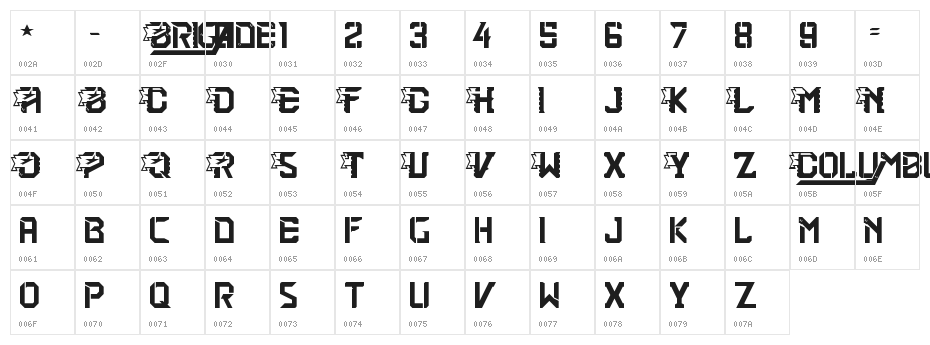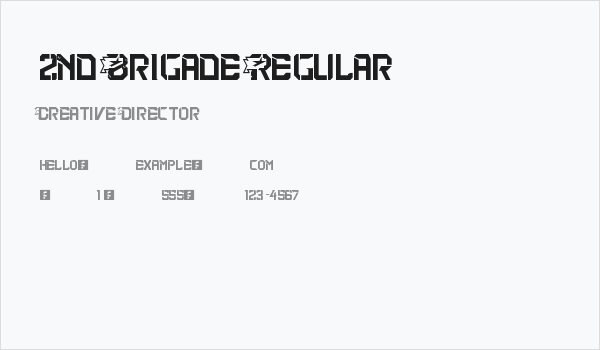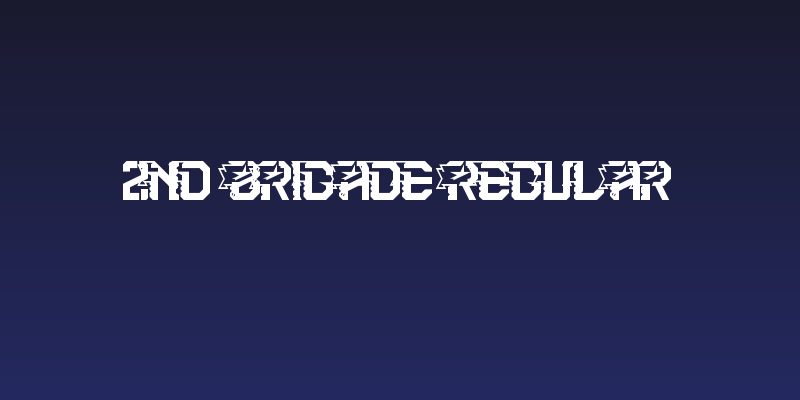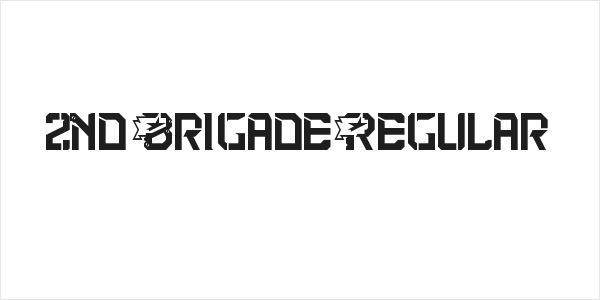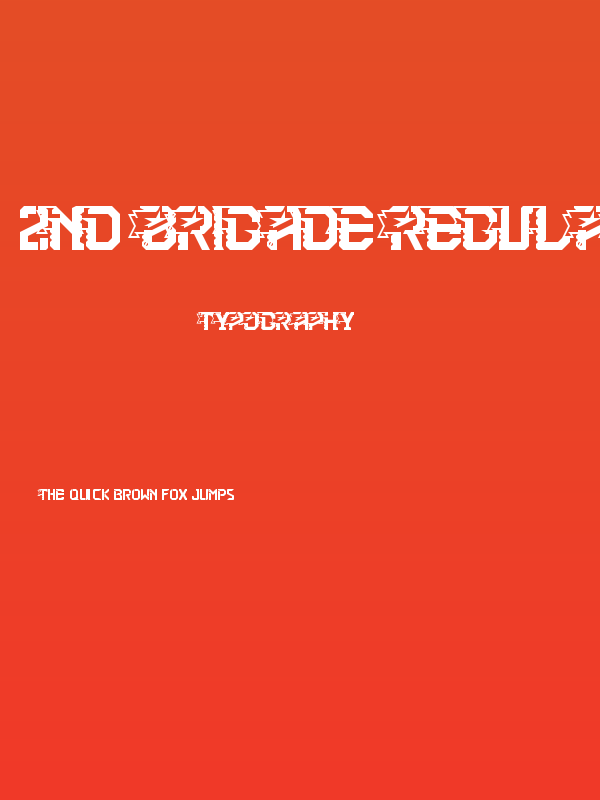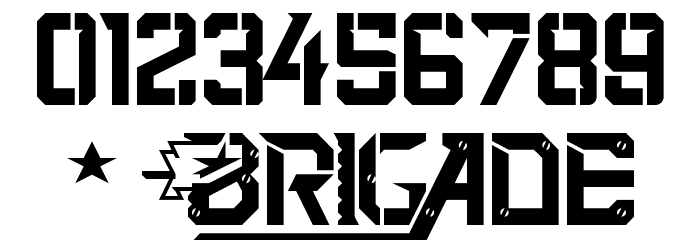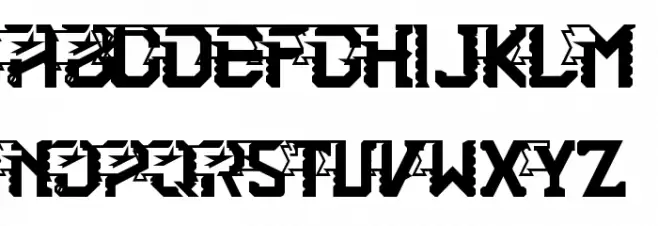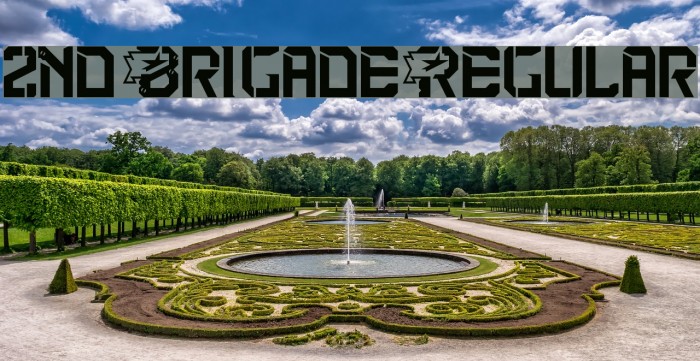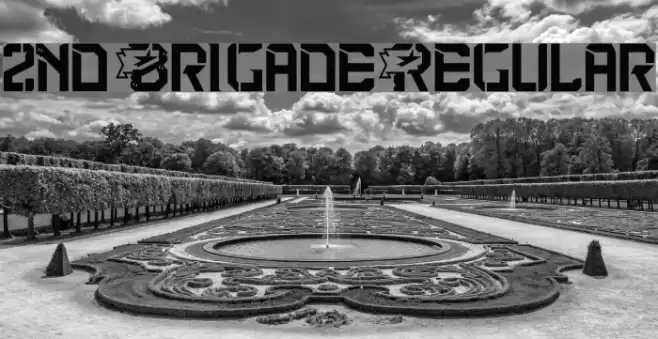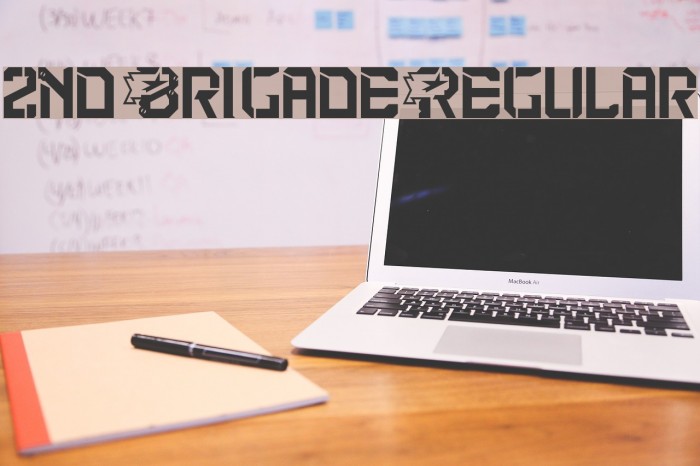
2nd Brigade Regular Font
✎ Stencil
Bill Walker
| Projets proposés | Ideal for military-themed posters, video game titles, branding for tactical gear, and sports team logos. |